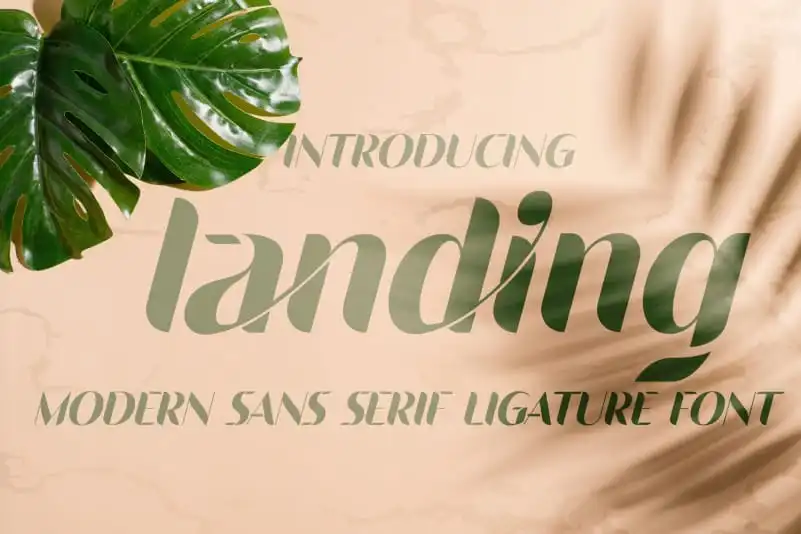
Landing Sans Serif Font – Download Grátis
Landing Sans Serif é uma fonte ligação sem serif que traz estilo único e impressionante para seus projetos de design. Esta fonte tem um contraste alto e é perfeitamente versátil, sendo ideal tanto para aplicações de marca como editoriais. No entanto, ela realmente brilha nos ambientes da identidade visual e editorial, onde o tipo se destaca por seu aspecto e sensação, tornando os designs agradáveis e fluídos. Com uma série de ligações únicas incorporadas, Landing Sans Serif é perfeito para designers que querem dar um toque diferenciado a suas criações. A 177Studio criou esta fonte sem serif de ligação como uma opção versátil para aplicar em diversos projetos do design, garantindo consistência e expressividade em cada projeto.